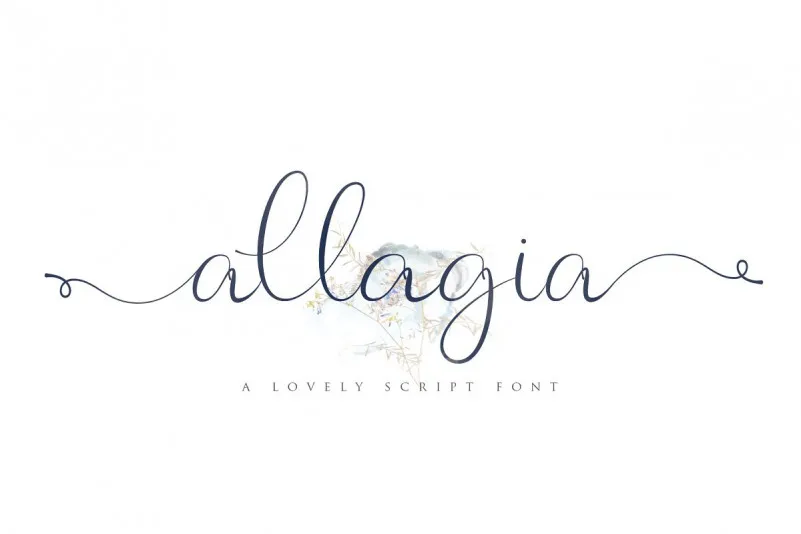
Allagia Script Font – Download Grátis
Esta fonte script é perfeitamente adequada para projetos de design que exigem um estilo elegante e natural. O Allagia Script Font traz a característica única do Allagia, com uma escrita quase autêntica que se destaca em todos os tipos de aplicação gráfica, desde logomarcas e identidade visual até convites, materiais de decoração para casamentos, postagens nas redes sociais, anúncios, embalagens de produtos, painéis, design fotográfico ou até mesmo marcas e círculos de água. Com um traço natural do tipo de letra, este é perfeito para qualquer projeto que você possa imaginar, incluindo citações, moda e muito mais. Experimente a Allagia Script Font e traga elegância à sua próxima produção gráfica.